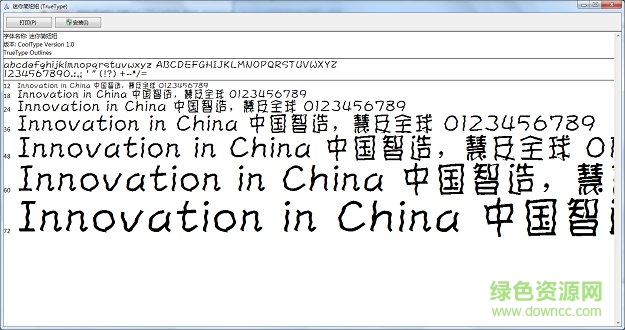
迷你簡(jiǎn)妞妞字體是一款提供給需要進(jìn)行文字編輯,媒體創(chuàng)作用戶免費(fèi)使用的字體文件,通過(guò)進(jìn)行安裝使用用戶能夠?yàn)槲淖指黝愶L(fēng)格與藝術(shù)效果,創(chuàng)作出比較舒適的字體形式!
迷你簡(jiǎn)妞妞的字體風(fēng)格是帶有扭曲效果的字體樣式,給你一種全新的字體效果,快來(lái)體驗(yàn)吧!